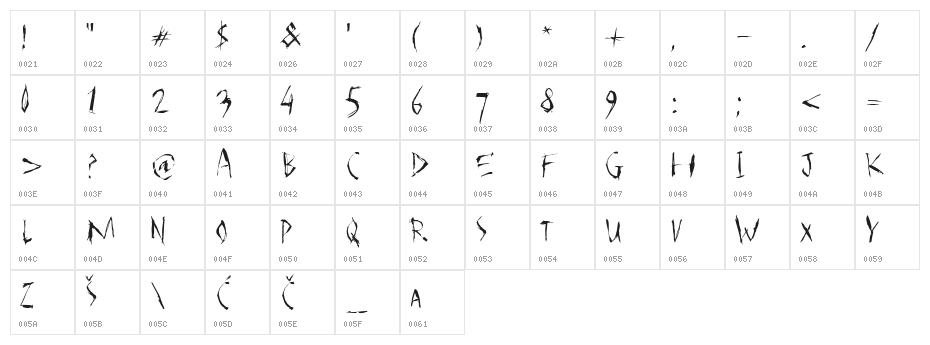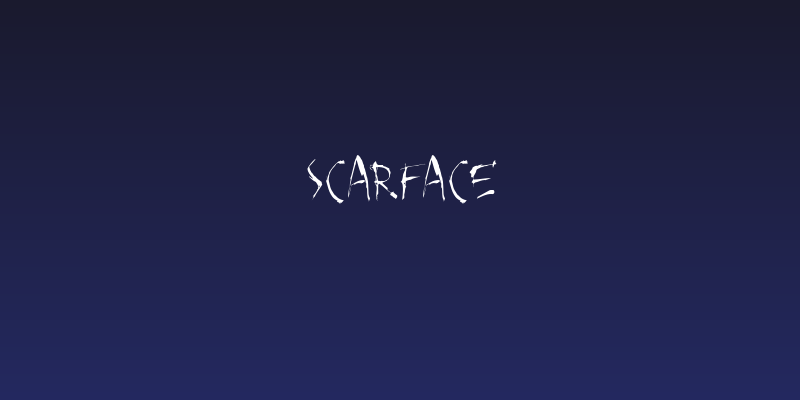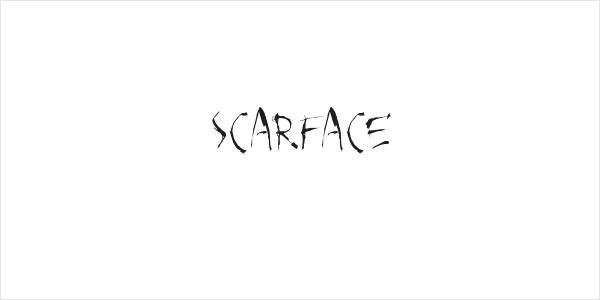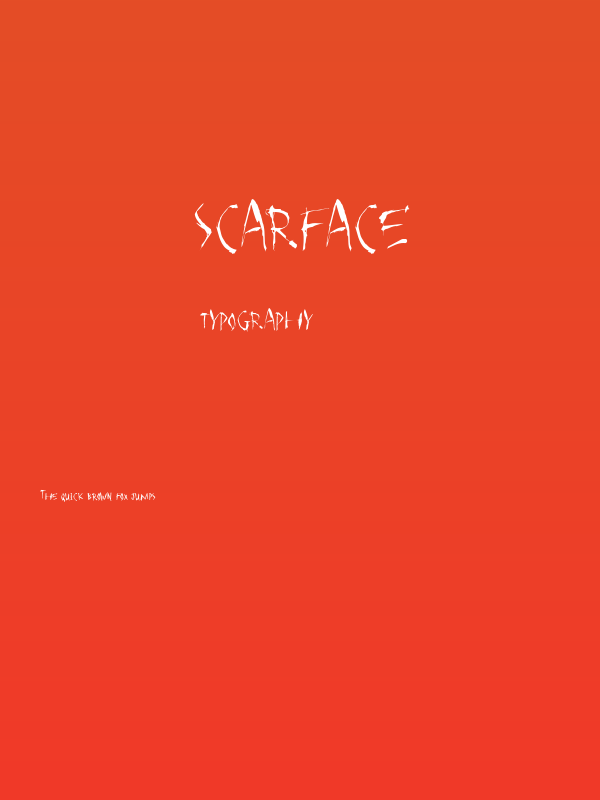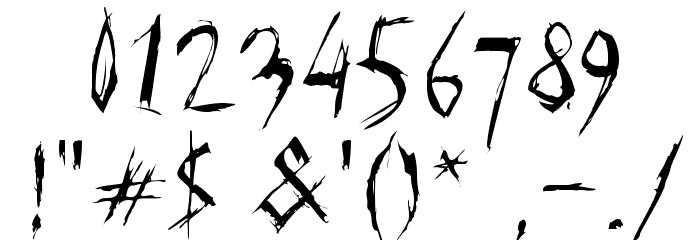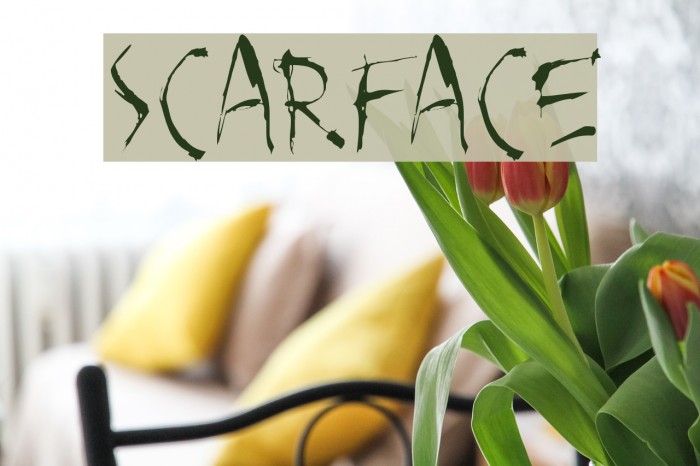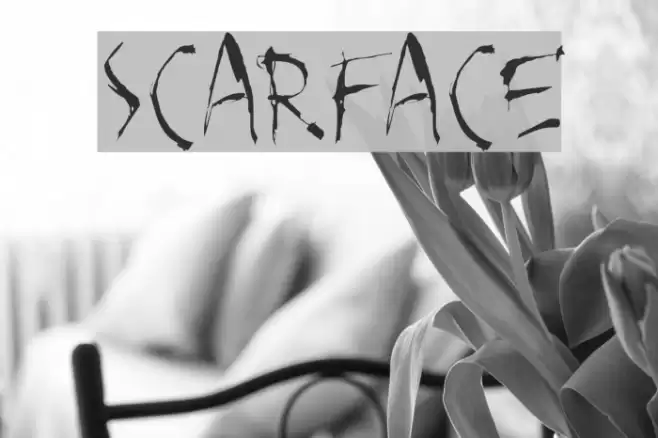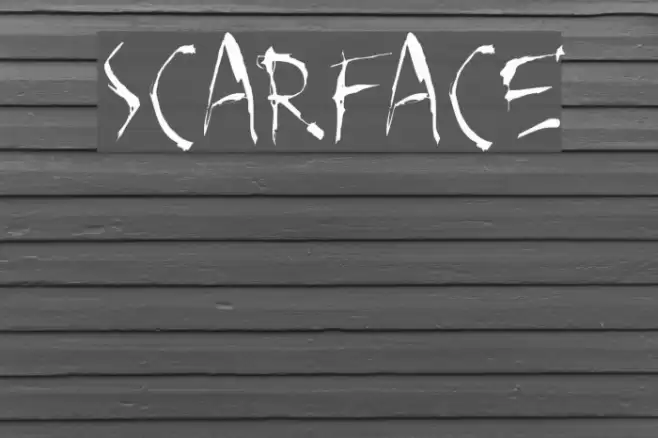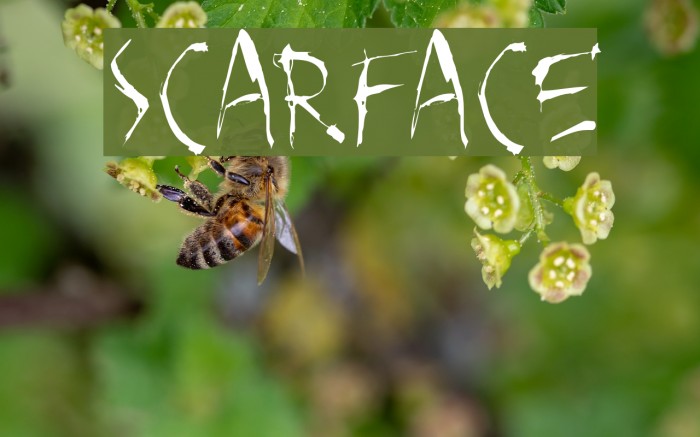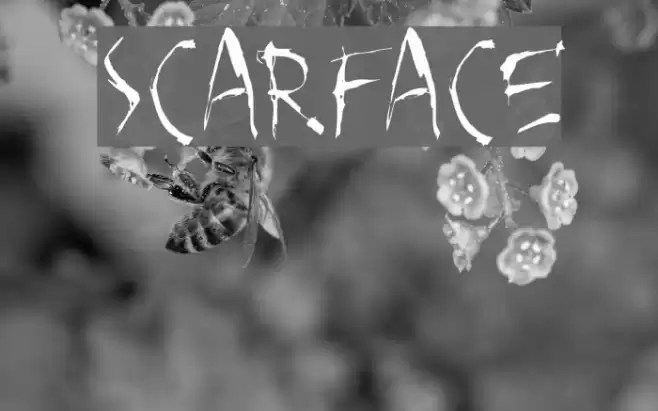
SCARFACE Font
| النمط العام | Edgy, Raw, Distressed |
| مشاريع مقترحة | Ideal for posters, album covers, branding for edgy products, and any project needing a bold, attention-grabbing look. |